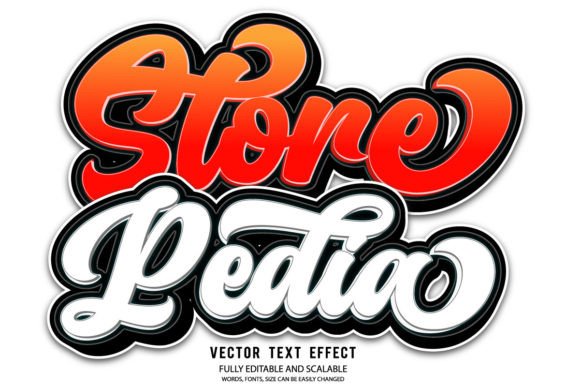
Store Pedia Editable Modern Lettering
Store Pedia Editable Modern Lettering์™€ ๊ฐ™์€ ๊ณ ํ’ˆ์งˆ ์ž์‚ฐ์„ ์ฐพ๊ณ  ์žˆ๋‹ค๋ฉด ์ด ํ”„๋ฆฌ๋ฏธ์—„ ํŒจํ‚ค์ง€๋Š” ์ฐฝ์˜์ ์ธ ํ”„๋กœ์ ํŠธ๋ฅผ ์œ„ํ•œ ํ™˜์ƒ์ ์ธ ์„ ํƒ์ž…๋‹ˆ๋‹ค.
์ •๋ฐ€ํ•˜๊ฒŒ ์ œ์ž‘๋œ Store Pedia Editable Modern Lettering๋Š” ๊น”๋”ํ•œ ๋ฒกํ„ฐ, ๋ถ€๋“œ๋Ÿฌ์šด ํƒ€์ดํฌ๊ทธ๋ž˜ํ”ผ ๋ฐ ์•ˆ์‹ฌํ•  ์ˆ˜ ์žˆ๋Š” ์ƒ์—…์šฉ ๋ผ์ด์„ ์Šค๋ฅผ ์ œ๊ณตํ•ฉ๋‹ˆ๋‹ค.